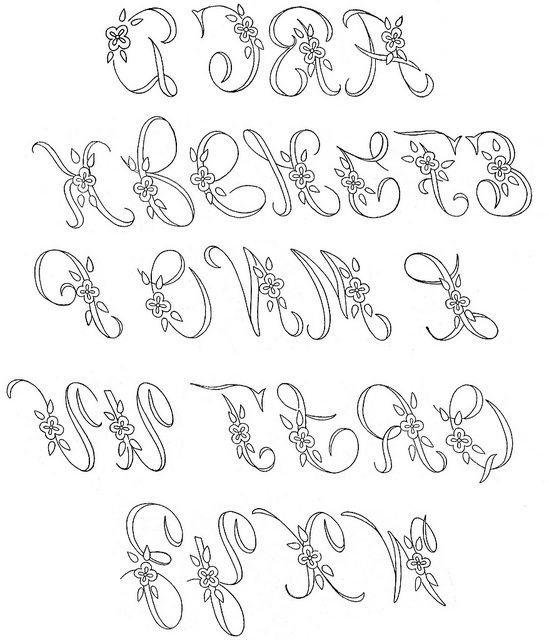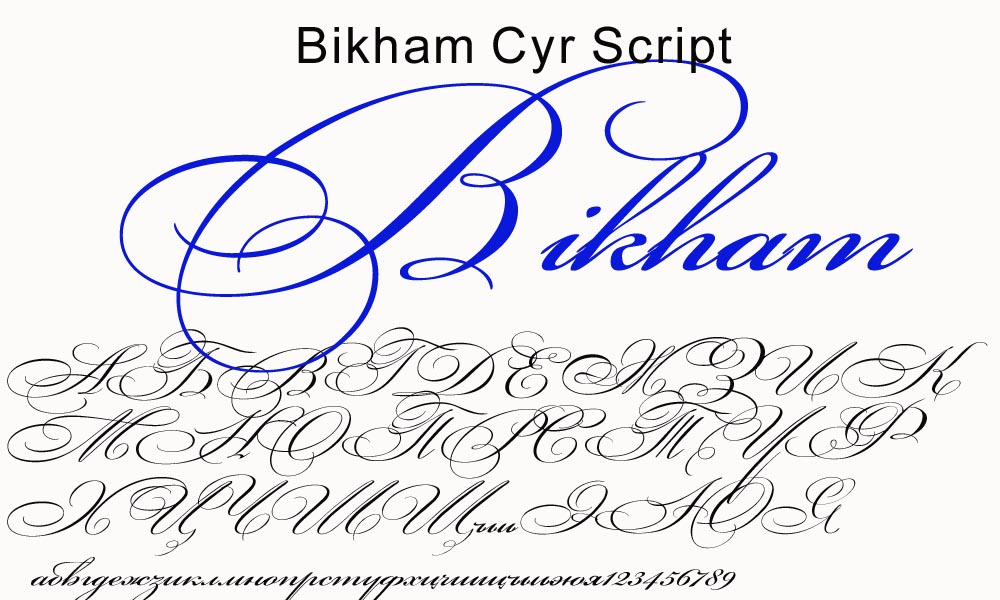
Старинные вензельные русские шрифты
25 скандинавских шрифтов, которые придадут вашим проектам скандинавский вид
Красивые вещи также могут выполнять свою функцию. Это именно тот принцип, который лежит в основе скандинавского движения, которое началось где-то в начале 20 -го -го века. То, что началось в странах Дании, Финляндии, Исландии, Норвегии и Швеции, распространилось по всему миру.
Сегодня скандинавская красота является синонимом полезности. Так что, если вы ищете великолепные, практичные элементы дизайна, обратите внимание на эти удивительные скандинавские шрифты.
Bjorn — дисплейный шрифт без засечек с острыми углами. Это универсальный скандинавский шрифт, в котором используются прописные многоязычные буквы, цифры и знаки препинания. Он поставляется в обычном, светлом и полутоновом стилях.
2. NoatunNoatun — это скандинавский шрифт с уникальным геометрическим стилем. Он отлично работает в заголовках, логотипах и коротких цитатах. Он включает в себя некоторую многоязычную поддержку, прописные буквы, цифры и знаки препинания.
3. NordicaПредставляем Nordica, нарисованный вручную скандинавский шрифт с красивым руническим стилем, который поможет вам привнести дух скандинавского региона в ваши дизайнерские работы!
4. Tundra Tundra — простой русский шрифт без засечек двух начертаний.
Он включает заглавные многоязычные буквы, цифры и знаки препинания.
5. Zenzero Grotesk — свежий, эксцентричный и стильный скандинавский шрифт, сочетающий в себе шрифты без засечек и плиты. Он может похвастаться множеством лигатур и альтернативных стилистических глифов для полного контроля над конечным результатом.
6. Скандинавский шрифт CastilloHappy Letters с гордостью представляет этот современный дисплейный шрифт в 4 уникальных стилях (обычный, жирный и курсив). С бонусом в виде 6 бесшовных шаблонов вы проведете часы веселья, работая над альбомами для вырезок, открытками, логотипами, этикетками, альбомами и подарочными упаковками.
7. Jonny Font Создано Alena Dubinets ( Alyonka_lis есть две версии шрифта De Corface ) используется самостоятельно.
Он также поддерживает символы латиницы и кириллицы, что дает вам больше свободы творчества.
8. Nordic TaleРасскажите свою историю, используя это красивое семейство шрифтов народного искусства из Виктория Струковская ( Struvictory.art ). Каждая буква из декоративной версии была сделана с использованием различных скандинавских узоров, рассказывающих свою собственную культурную историю. Пакет также включает в себя символы, так что вы будете рассказывать свои истории в превосходной гармонии.
9. Забавный рождественский шрифтНе можете дождаться самого чудесного времени года? С этим самоцветом из набора Qilli вам не придется этого делать! Пропитанный духом Рождества, уникальный шрифт поставляется со специальными символами, акцентами, альтернативами и лигатурами специально для вас!
Scandilover Это семейство латинских и кириллических шрифтов от Katsia Jazwinska было вдохновлено монохромной и черной скандинавской детской комнатой, наполненной рукописной графикой, а также детской комнатой в скандинавском стиле, наполненной рукописной графикой. белые аксессуары и принты. Доступны два шрифта (декоративный дисплейный шрифт и шрифт), используйте один или оба, чтобы раскрыть свою творческую сторону.
11. Lazy OlovРаскройте свою яркую сторону в этом предложении от JuliyArt . Представляя 3 удивительных шрифта в обычном, цветном и черном цветах, нет предела тому, что вы можете сделать. Пакет также включает в себя цветные и монохромные элементы, бесшовные узоры и постеры, которые помогут вам раскрыть свои творческие способности!
Скачать Lazy Olov
12. Храбрый Ульрик Если вы делаете что-то для праздников или для детей, вам понравится этот универсальный скандинавский шрифт из Катринелли .
Обычная версия с бесплатным шрифтом Doodle Symbol — это все, что вам нужно, чтобы начать создавать проекты в скандинавском стиле в кратчайшие сроки.
Скачать Brave Ulrik
13. Шрифт Hygge ScandinavianДобавьте датскую и норвежскую концепцию Hygge в этот шрифт от Alisovna 9. С его теплой и уютной атмосферой он будет потрясающе смотреться на рубашках, открытках, подушках, этикетках, плакатах, заголовках и многом другом.
Скачать шрифт Hygge Scandinavian
14. Скандинавский шрифт YetiJuliyArt делает черно-белое изображение таким красивым в этом шрифте, который поставляется в двух симпатичных стилях (обычный и полужирный). Получите набор, а также получите бонусы, такие как декоративные элементы, бесшовные узоры и постеры.
Скачать шрифт Yeti Scandinavian
15. Семейство скандинавских шрифтов Вдохновленный скандинавским фольклором и традиционным финским и шведским народным искусством, Favete Art с гордостью представляет это семейство шрифтов, которое представлено в двух уникальных версиях (декоративная и черная).
С черно-белыми скандинавскими символами в придачу, это тот набор, без которого вы не захотите обойтись!
Загрузить семейство скандинавских шрифтов
16. Шрифты SweetheartВыражайте свою любовь в любое время года, используя этот набор из Red Ink . Вы не только получите классные шрифты в 3 красивых стилях, но также получите более 100 нарисованных от руки иллюстраций любовных клипов в цвете, а также контурные иллюстрации любовных клипов в черном цвете.
Скачать Sweetheart Fonts
17. Детские шрифты Little SubmarineЗаставьте малышей улыбаться с помощью этого удивительного шрифта, созданного KAZUKA . Он доступен в двух стилях (обычный и декор), которые раскроют в вас ребенка. Он идеально подходит для детских проектов, таких как персонализированные предметы и наклейки на стены.
Загрузить детские шрифты Little Submarine
18.
Шрифт Ethnic Love Latin Vibes хочет, чтобы вы вышли и поиграли с этим набором «все-в-одном» с совершенно уникальным декоративным шрифтом! Получите его сегодня и наслаждайтесь другими бонусами, такими как кисти иллюстратора (совместимые только с Illustrator CC+), бесшовные узоры и декоративные круги.
Скачать шрифт Ethnic Love
19. Janica FontПридайте своим проектам теплоту с помощью этого семейства шрифтов, в котором много скандинавских фольклорных элементов. Предоставленный вам Katrinelly , шрифт доступен в двух стилях (обычный и черный), которые отлично сочетаются друг с другом или используются по отдельности. Пакет также содержит бонусные символы для завершения вашего конечного продукта!
Скачать шрифт Janica
20. Maitana Развлекайтесь, используя этот шрифт от himoki . Благодаря игривому деревенскому стилю, представленному в двух версиях (Extralight и Light), а также дополнительным дудлам, он станет отличным дополнением к любому проекту, которому нужна смелая скандинавская атмосфера.
Скачать Maitana
21. Шрифт Norse (БЕСПЛАТНО)
Джоэл Карруш с гордостью представляет этот сильный, бескомпромиссный шрифт, рожденный в стране Vikings. Это на 100% бесплатно для личного и коммерческого использования (но пожертвования принимаются с радостью). Он должен улучшить как современные, так и традиционные проекты своим минималистским видом, но тонкими грубыми линиями.
Скачать шрифт Norse
22. Шрифт Stormning (БЕСПЛАТНО)Это удивительное семейство шрифтов из KineticPlasma Fonts (разработано совместно с Mew Too ) включает 12 стилей, каждый со своими глифами. Он состоит в основном из рун Старшего и Младшего Футарка, а также далекарлианских (шведская провинция) и средневековых скандинавских рун в качестве эквивалентов латинским символам, не имеющим эквивалентов в рунических алфавитах.
Скачать шрифт Stormning
23.
Folkard (БЕСПЛАТНО) Придайте своим обложкам книг, названиям игр и футболкам нотку старинной магии с помощью этого сказочного шрифта с засечками от The Scriptorium . В нем есть символы верхнего и нижнего регистра, а также цифры и знаки препинания.
Скачать Folkard
24. Художественный набор «Скандинавские руны» (БЕСПЛАТНО)Добро пожаловать в загадочный мир скандинавских викингов! Эта замечательная коллекция от Draw Wing Zen содержит рунический алфавит в формате PNG, а также иллюстрации кристаллов, алхимических символов, трав и мазков кисти. Дайте волю своему творчеству, настроив их или комбинируя с другими произведениями искусства. Возможности безграничны с этим комплектом!
25. Nordic (БЕСПЛАТНО) Основанный на скандинавских рунах и элегантных геометрических формах, этот уникальный шрифт из Yana Bereziner соответствует вашим потребностям.